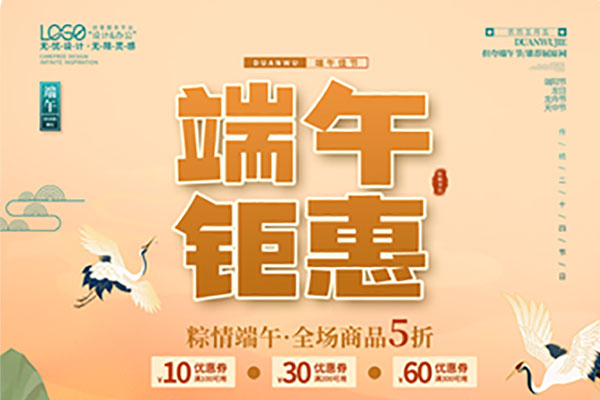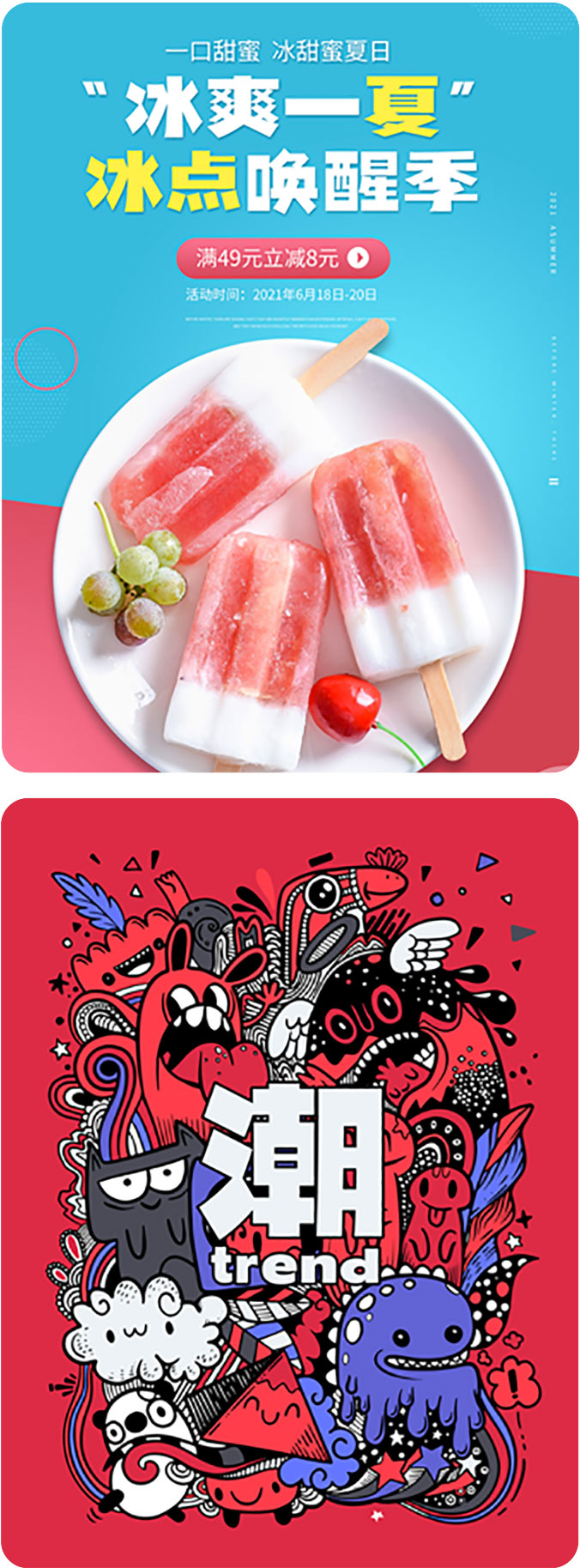
千图厚黑体
千图厚黑体:免费商用字体,力量与美感的完美结合
千图网精心打造的千图厚黑体是一款免费商用字体,以其独特的魅力引领了设计潮流。这款字体以粗犷有力的笔画和宽扁字型的组合,构建出稳重且充满力量的形态,展现出独特的个性。
在笔画细节上,千图厚黑体精致的修饰不仅提升了字体的设计感,更在不经意间增添了一抹精致的美感。中宫的饱满使得文字间的排版组合更加醒目耐看,为你的设计增色添彩。无论是活动海报还是品牌活动的标题,千图厚黑体都能让你在众多设计中脱颖而出。
千图厚黑体,一款充满力量与美感的免费商用字体,是你设计中不可或缺的好帮手。现在就让我们一起,用千图厚黑体打造出独具匠心的作品吧!
千图厚黑体效果预览
千图厚黑体字体效果预览